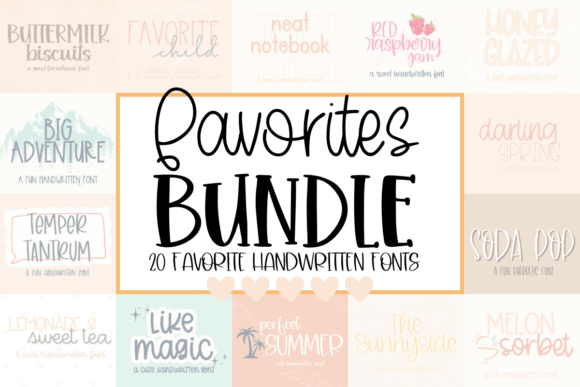
Favorites Font Bundle
適切なデザイン要素を見つけるのは難しい場合がありますが、Favorites Font Bundleは作品を即座に引き立てる優れたコレクションを提供します。
POD(オンデマンド印刷)製品、結婚式の招待状、またはソーシャルメディアのグラフィックを作成している場合でも、Favorites Font Bundleは理想的です。